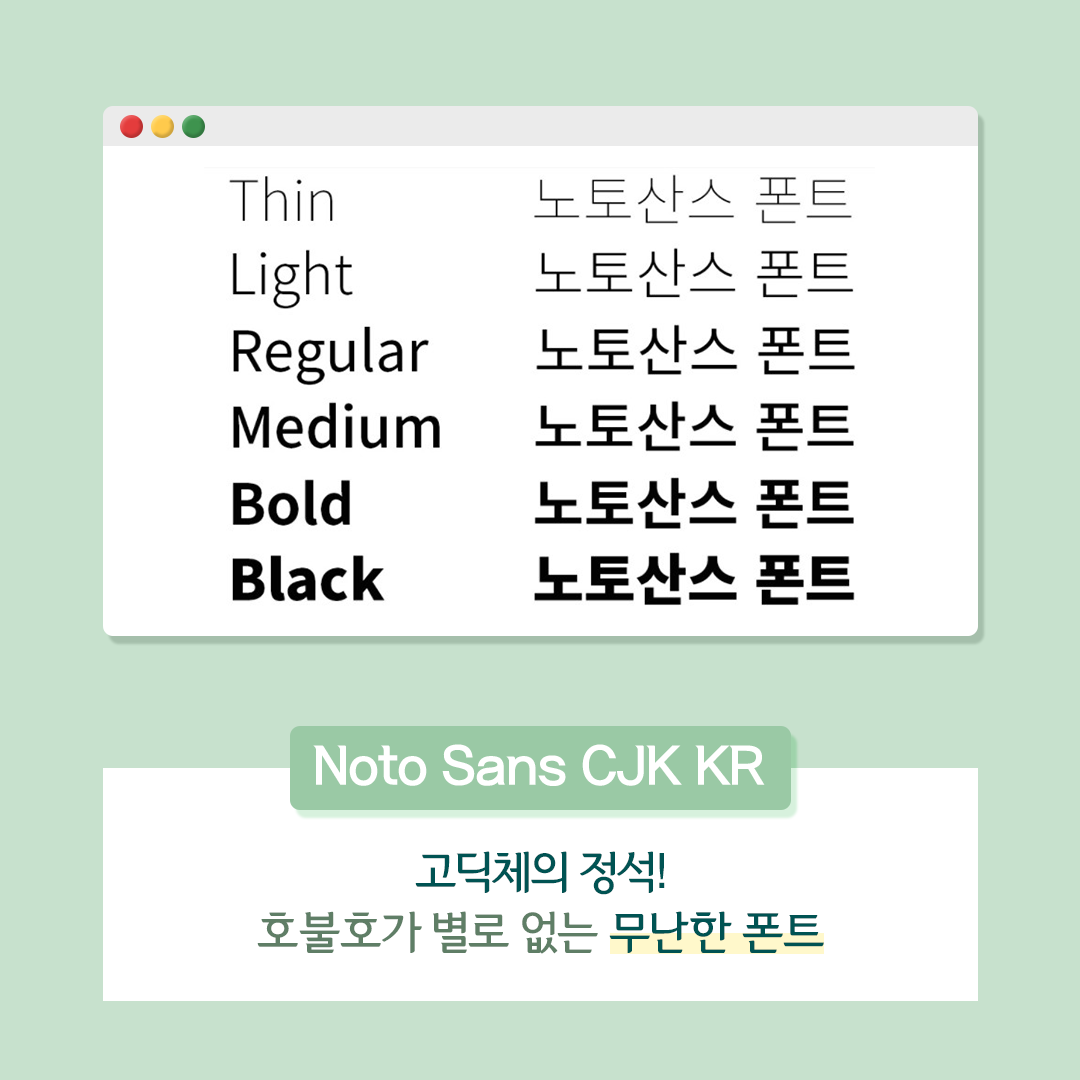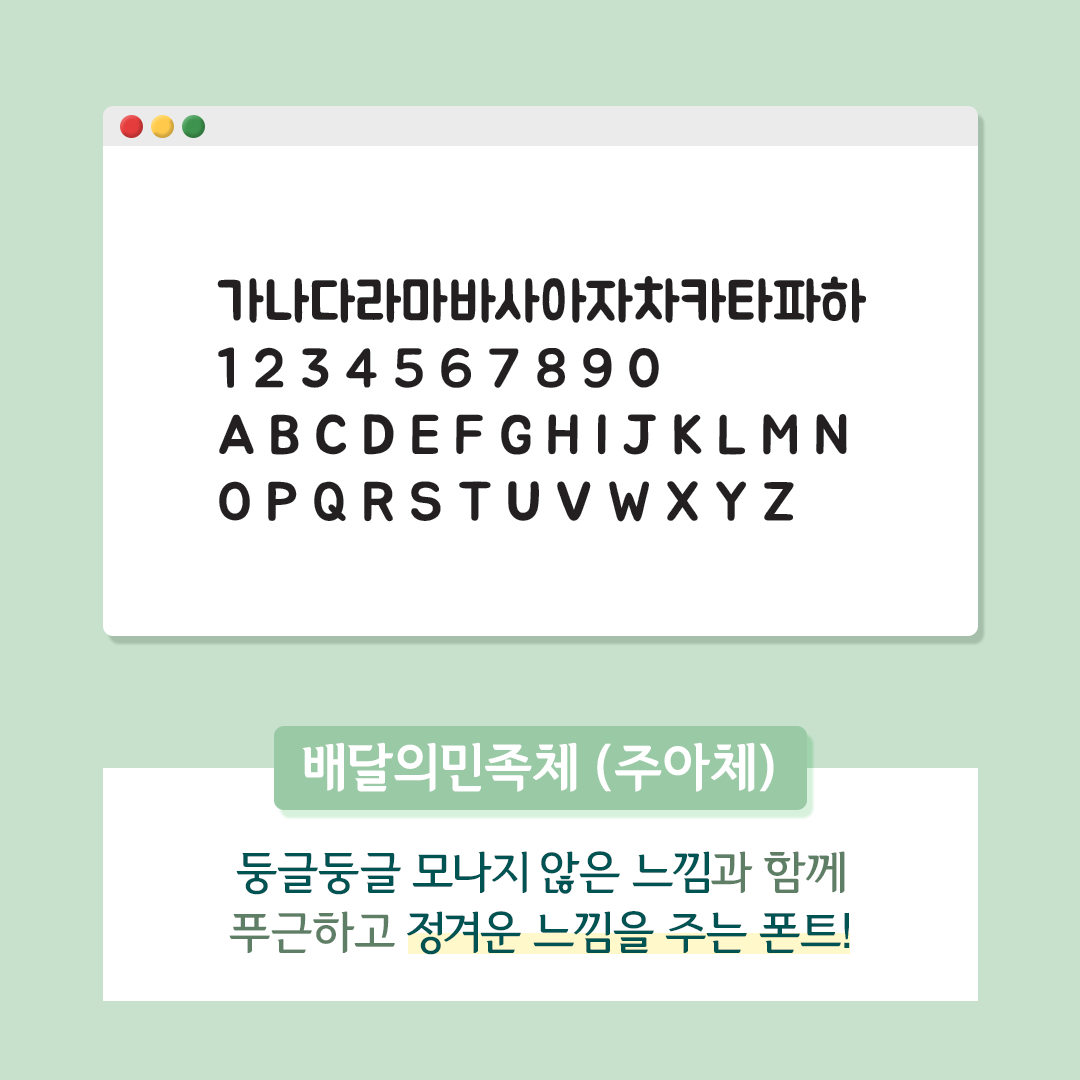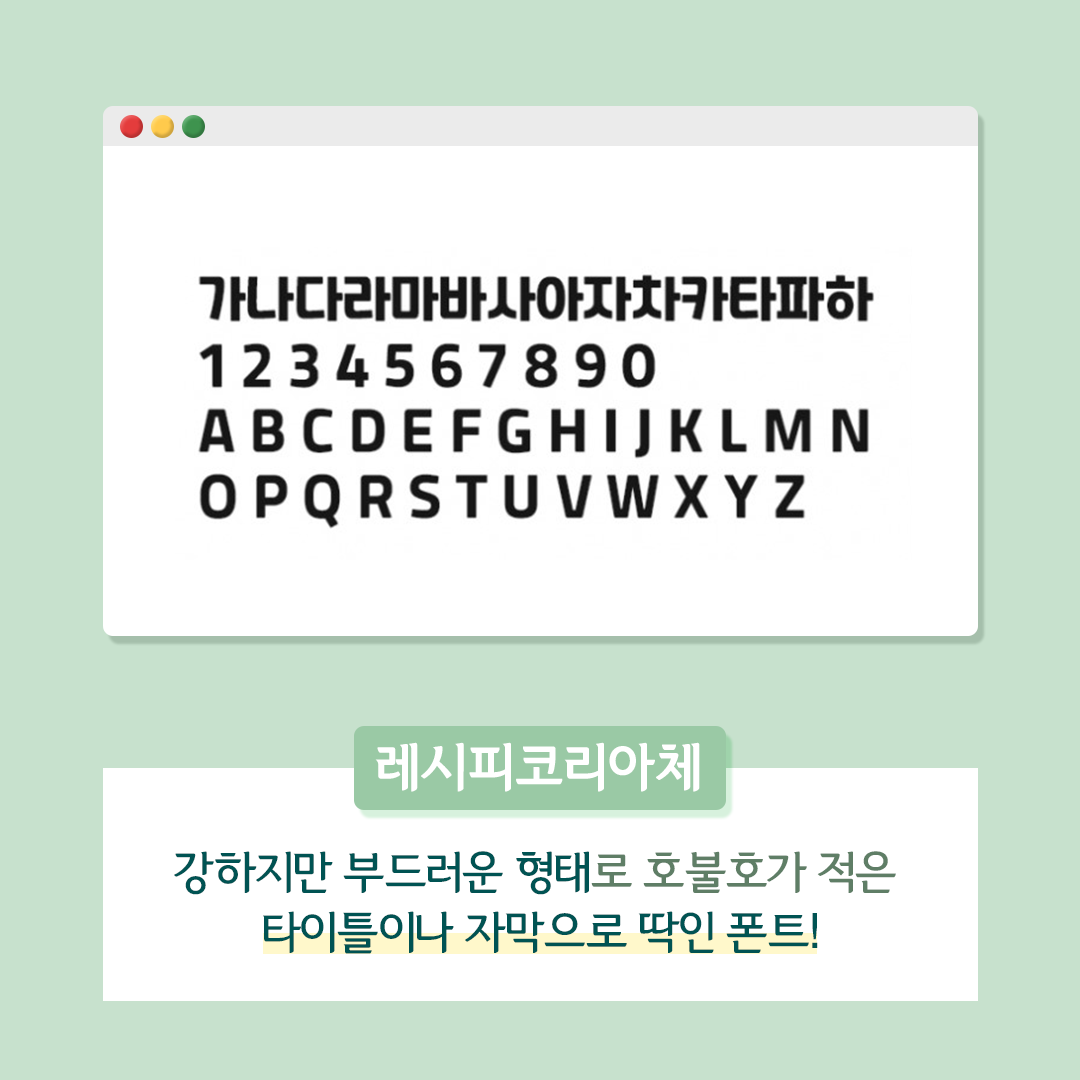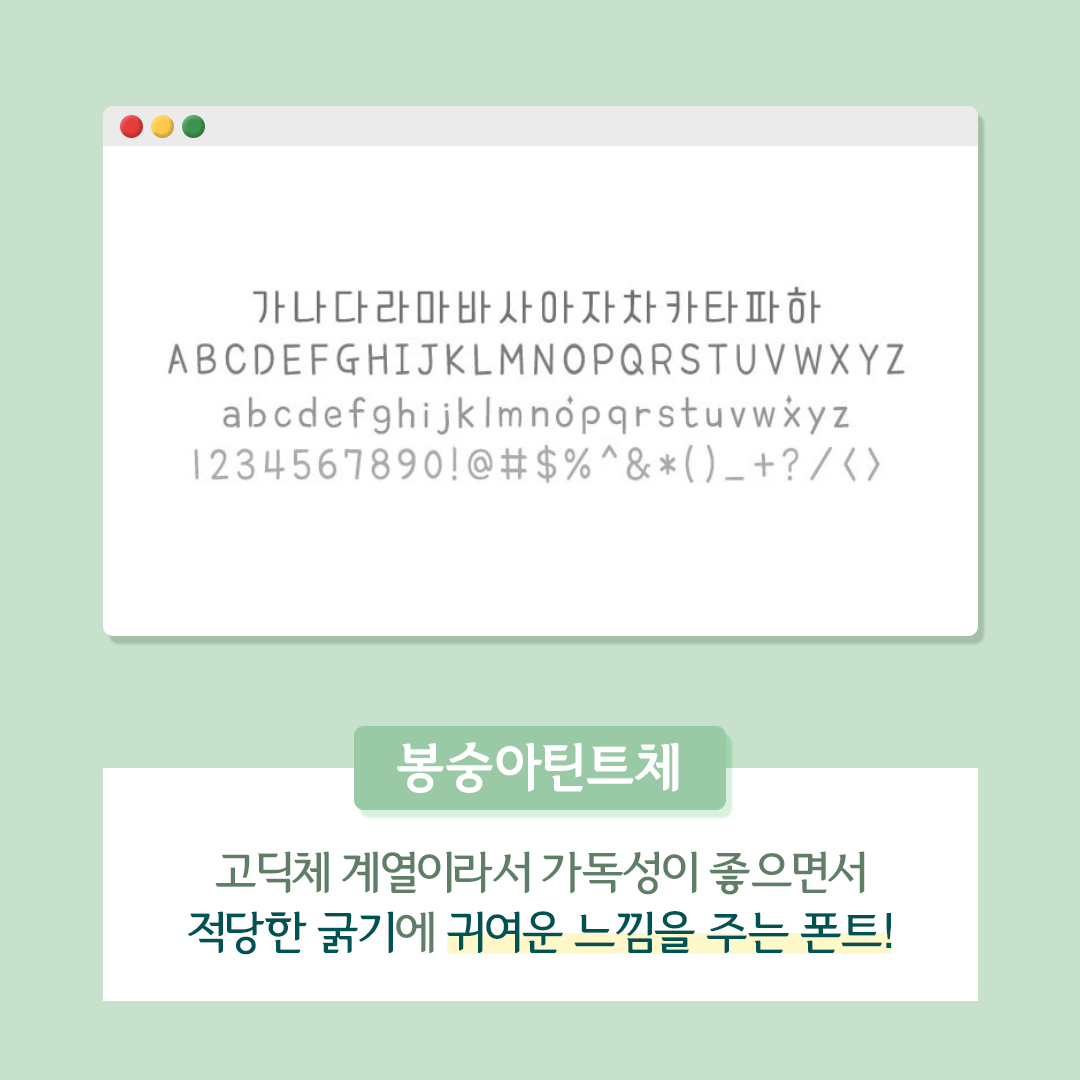
저작권 걱정 NO! 상업용 무료 폰트 추천
01. Noto Sans CJK KR
고딕체의 정석이라고 불리는 노토산스입니다
호불호가 없는 무난한 폰트로,
가독성이 좋고 단정한 느낌이 들어 자주 사용되는 폰트입니다.
02. 배달의 민족 주아체
모나지 않은 느낌을 주면서, 정겨운 느낌을 주기 때문에
대화의 자막이나 V로그의 귀여운 느낌을 표현하는데 주로 사용됩니다.
03. 레시피코리아체
강하고 강렬한 느낌 속에 부드러움이 들어있는 레시피코리아체는
영상의 타이틀이나 소개하는 영상의 자막으로 사용하기에 좋을 것 같습니다
04. 레시피코리아체
05. 봉숭아틴트체
봉숭아틴트체는 앞서 말씀드린 폰트와 비슷한 고딕체 계열이라
가독성이 좋으면서 과하지 않은 적당한 굵기에 둥근드낌을 가지고 있어
귀여운 느낌을 주는 폰트입니다.